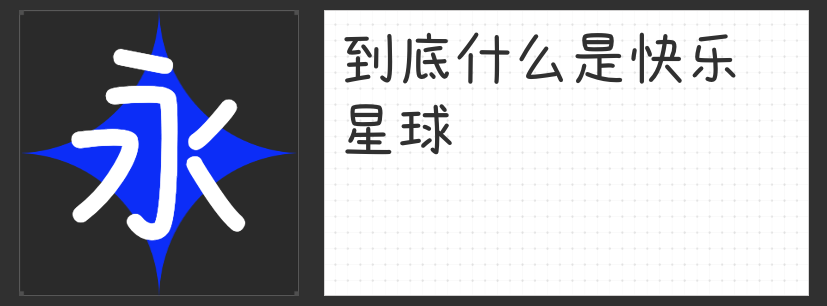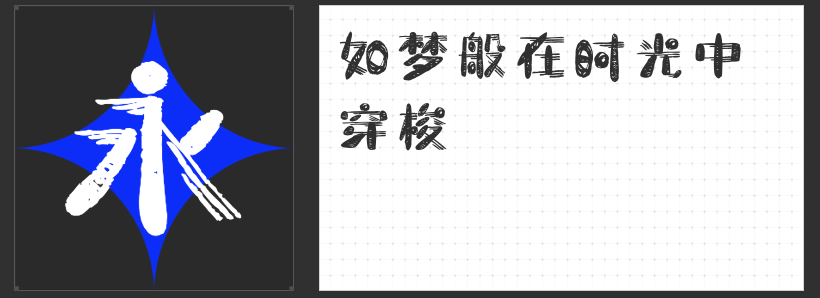
四款宝藏商用动漫字体,解锁设计新次元!
在动漫设计与创意海报的领域,字体不仅是信息载体,更是氛围营造的关键。今天推荐四款风格迥异却同样惊艳的商用动漫字体,助你轻松打造视觉爆点!
1. 字恋狂白日梦简
这款字体以“做梦”为灵感,笔画如被风揉乱的丝带,在时光中肆意穿梭。看似无序的线条中藏着孩童涂鸦的天真,适合绘本内页、漫画对话框或奇幻主题的标题设计。其慵懒随性的气质,能瞬间将观众拉入童话般的异想世界。
2. 造字侠灵霄简繁 传神
取名自《西游记》中玉帝的居所“灵霄宝殿”,这款字体以硬笔手写为基底,笔画如刀刻般利落,字形古风劲萧却饱满均匀。无论是网游海报的热血标题,还是仙侠小说的封面书名,它都能以沉稳的结构与劲健的笔力,传递出仗剑天涯的豪迈气场。
3. 字恋狂灵珑简
横细竖粗的反差设计,搭配稚嫩如孩童的笔触,这款字体像极了随手涂鸦的创意手账。不规则的填涂痕迹与圆点点缀,让文字仿佛从漫画格中跳跃而出,尤其适合儿童品牌、萌系IP或轻松幽默的场景标题,瞬间拉满可爱值!
4. 字圈也字快乐星球体
横斜竖直、左低右高的字形结构,搭配钝角与直角的折笔设计,这款字体如少年般棱角分明。时而圆润时而尖锐的笔画,传递出“不迎合、只做自己”的叛逆态度。适合青春题材海报、潮玩品牌或需要强调个性的视觉设计,让文字成为表达态度的利器!